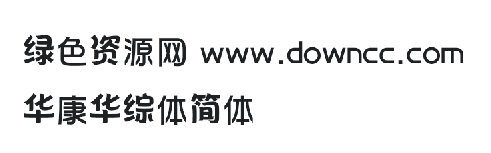
華康華綜體簡是一款適合商業(yè)用途的字體,常見于廣告標(biāo)語,圖書作品上。歡迎來綠色資源網(wǎng)下載這款字體。
華康華綜體字體是一款用于海報設(shè)計方面的字體,本作品可用于出版印刷字體、廣告設(shè)計字體、網(wǎng)頁設(shè)計字體、包裝設(shè)計字體、 屏幕顯示字體等